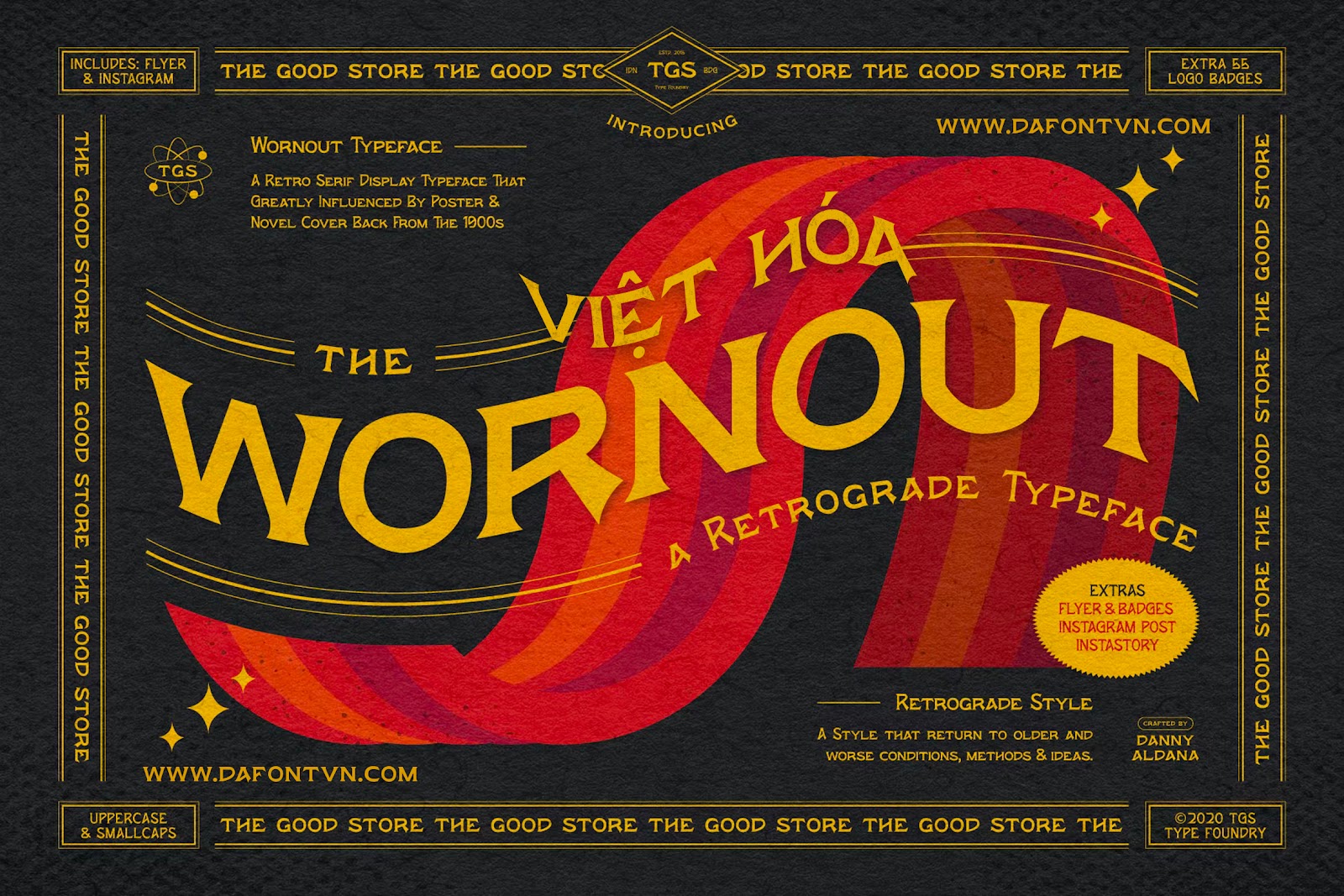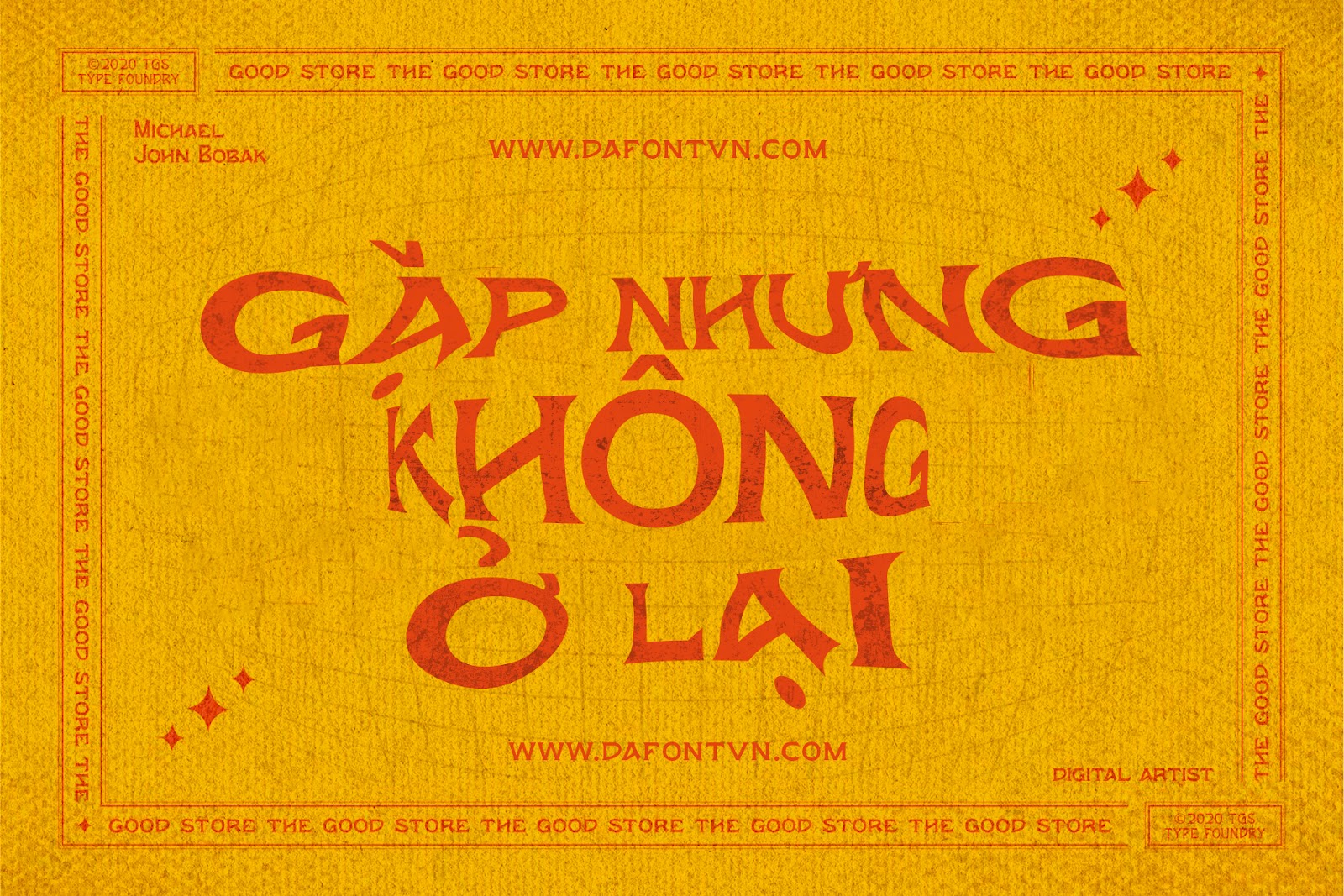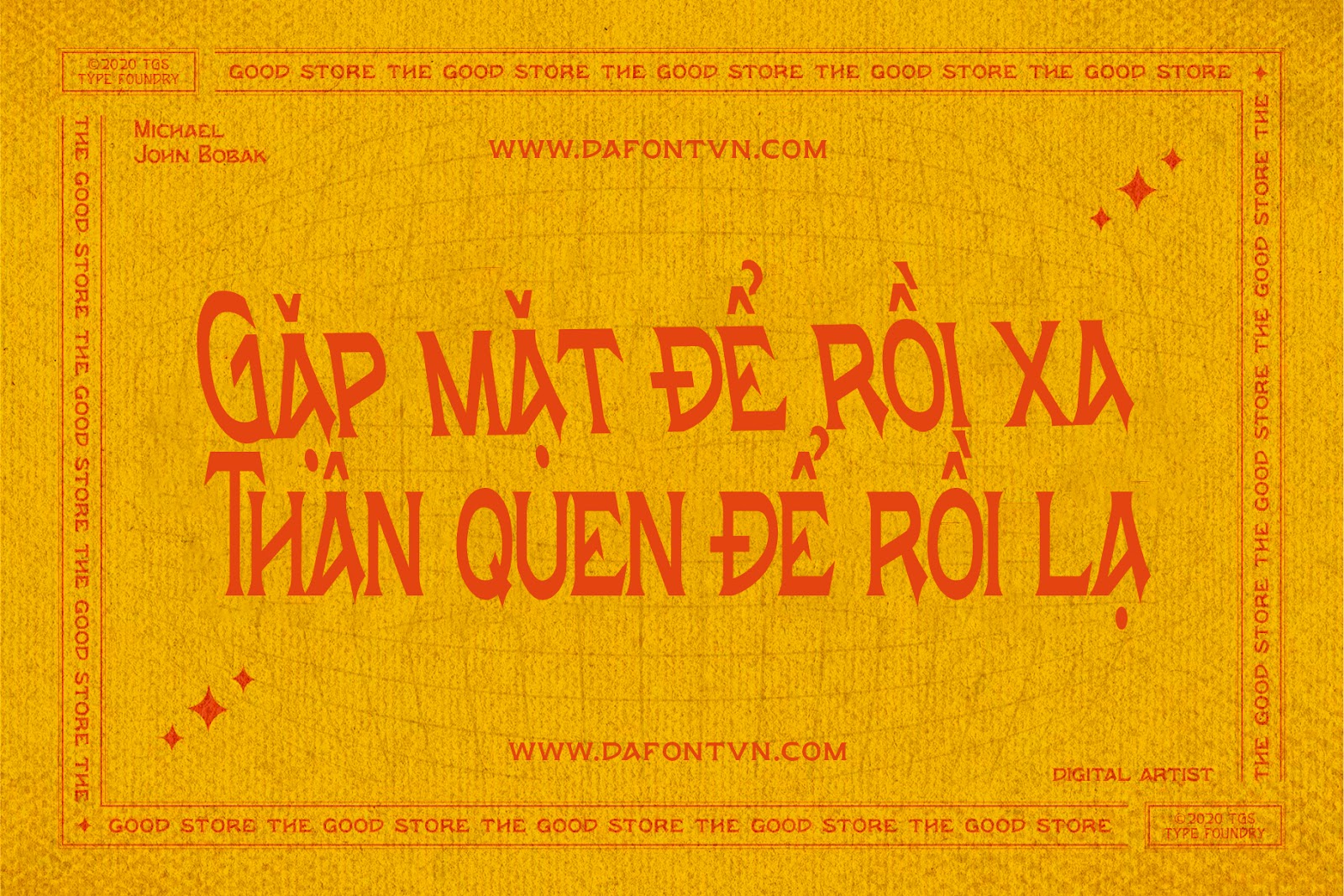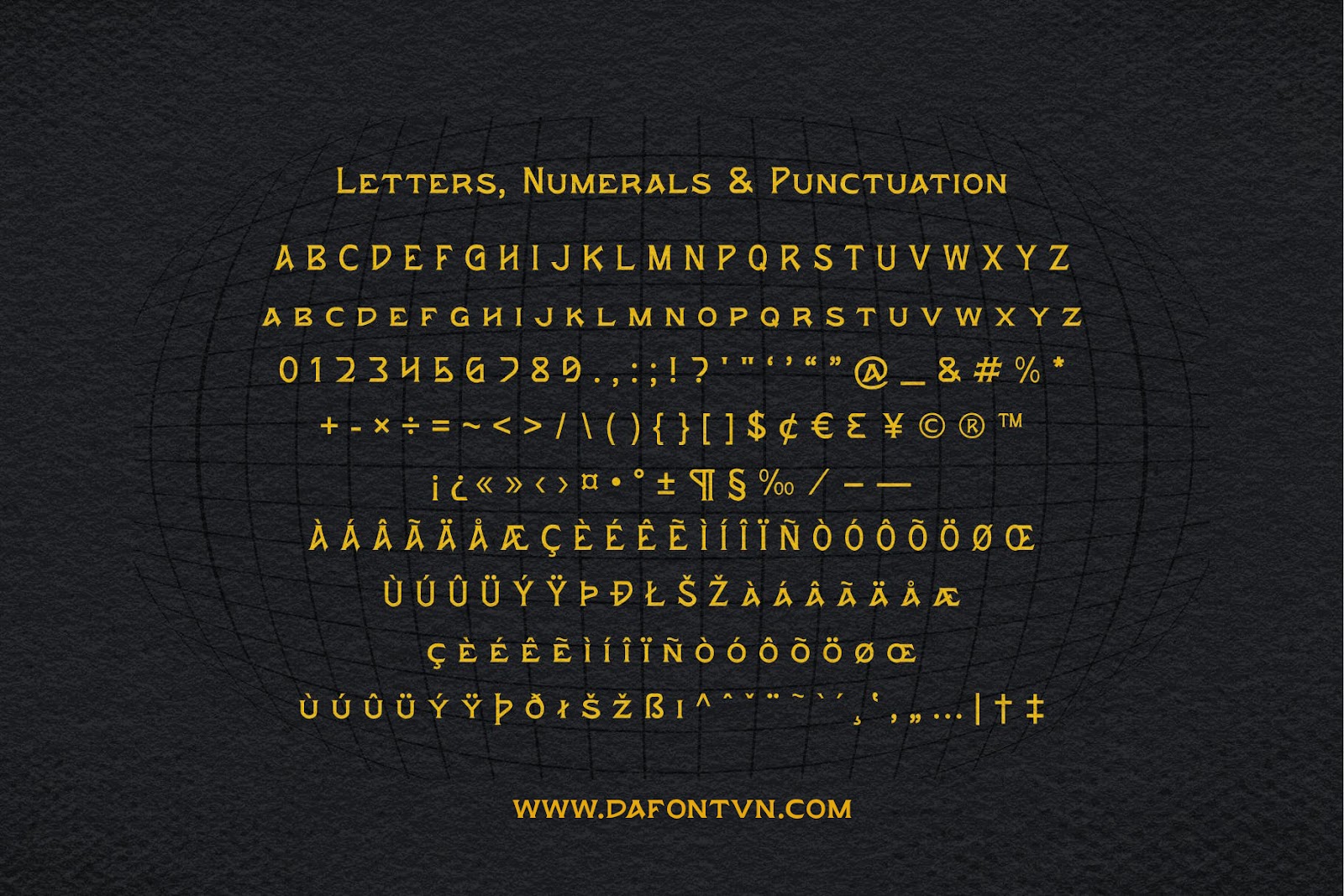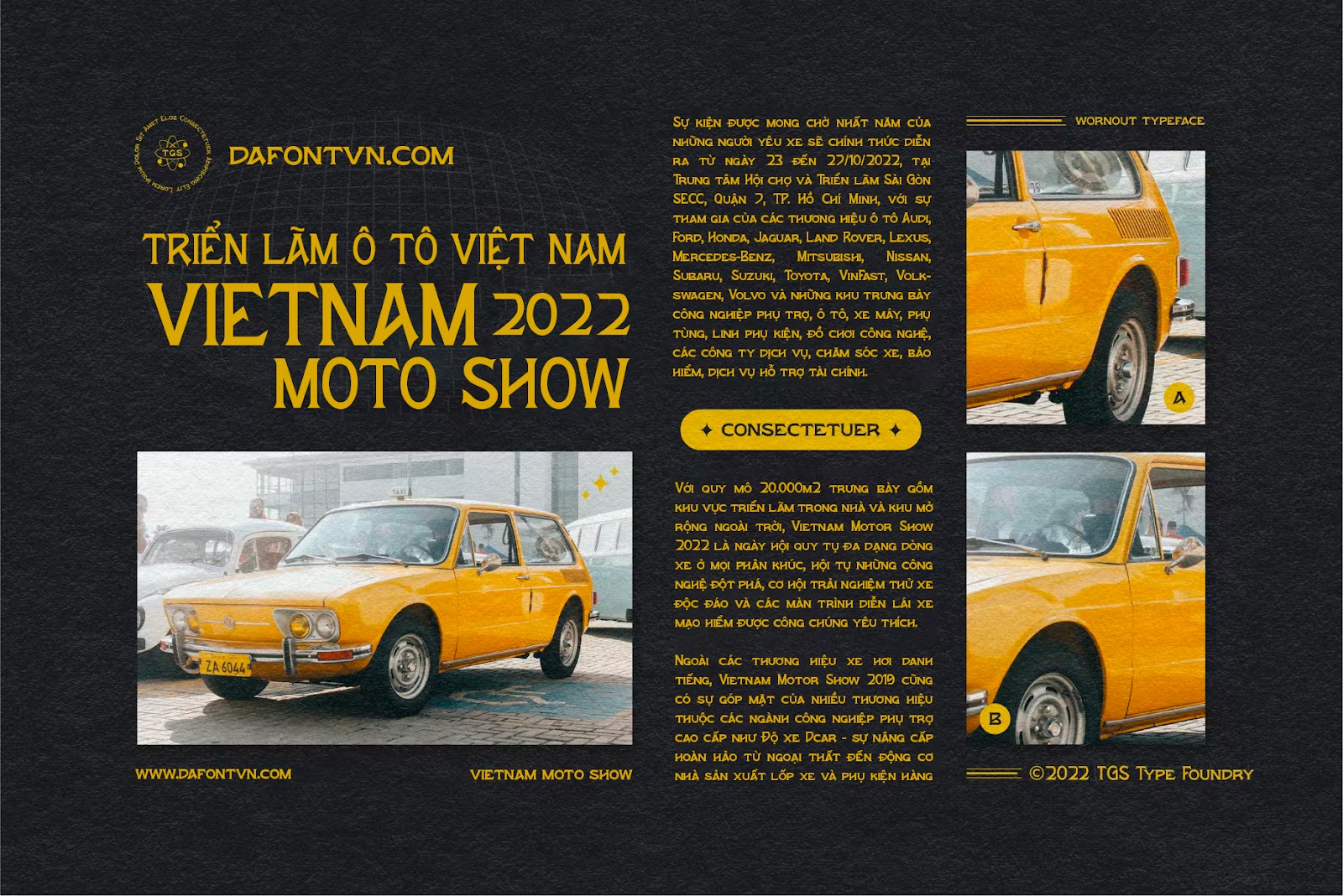
Font việt hóa Wornout Typeface – 1 chiếc font retro
Font Wornout Typeface Việt Hóa là một phông chữ đậm chất retro được lấy cảm hứng từ nhiều áp phích và bìa những cuốn tiểu thuyết từ những năm 1900. Phông chữ mang tính xưa cũ khá phù hợp cho các thiết kế cổ điển, vintage, banner, quảng cáo…